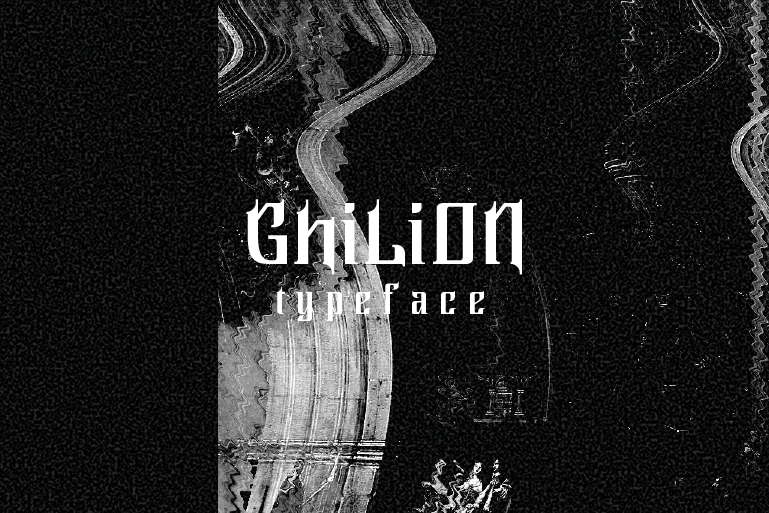
Ghilion Typeface – Download Grátis
A Ghilion Typeface é uma fonte inspirada num documento americano do século XX com influências góticas. Desenhada por Valent, essa tipografia geométrica e modernizada se adapta perfeitamente para as necessidades de uso contemporâneo. Sua natureza clara e acentuada faz dela um recurso ideal para títulos em designs visuais. Seja em cartazes, posters ou materiais de marca digital, Ghilion oferece uma combinação perfeita de elegância e simplicidade, adaptável às mais variadas necessidades gráficas do nosso dia a dia no Brasil.